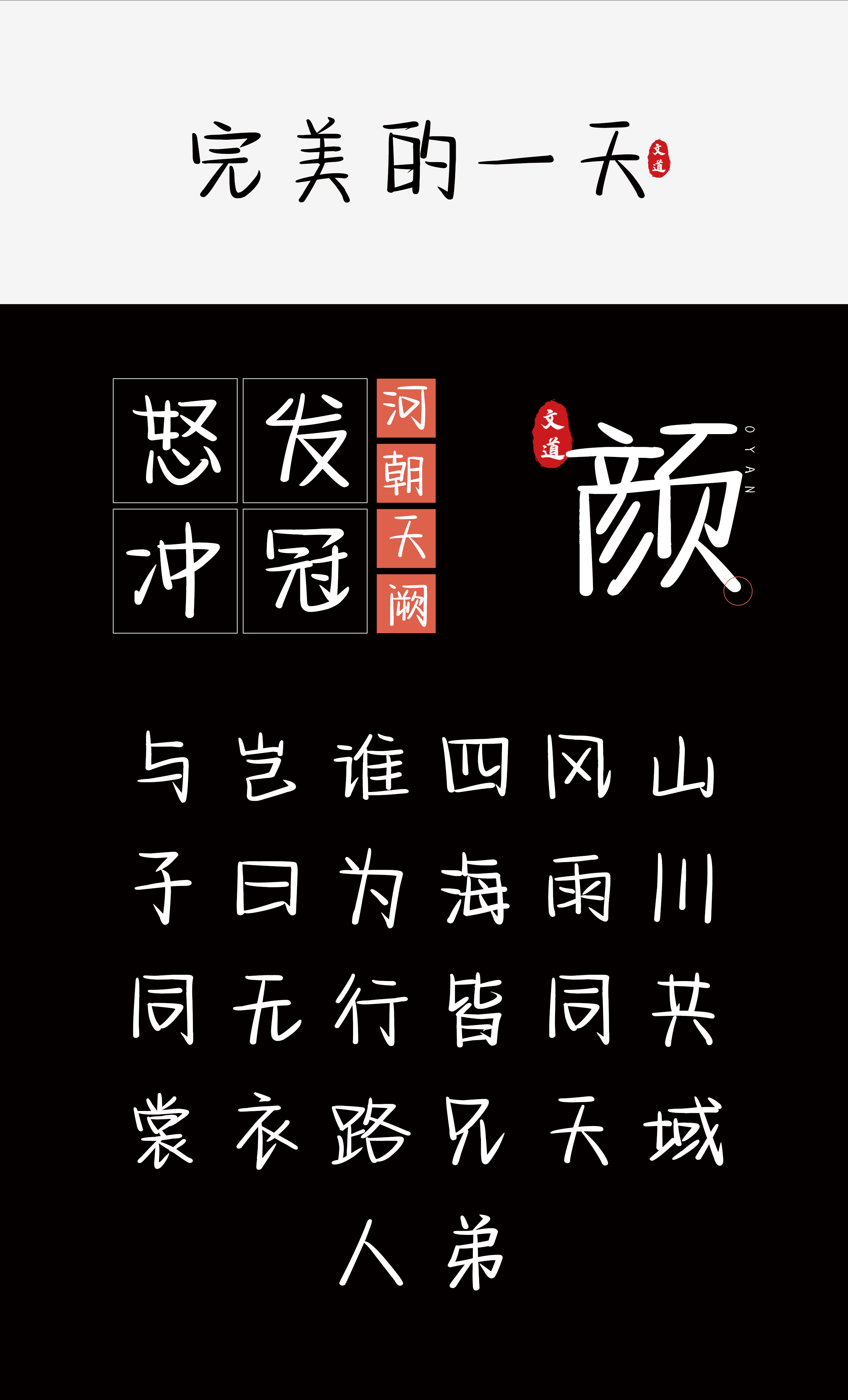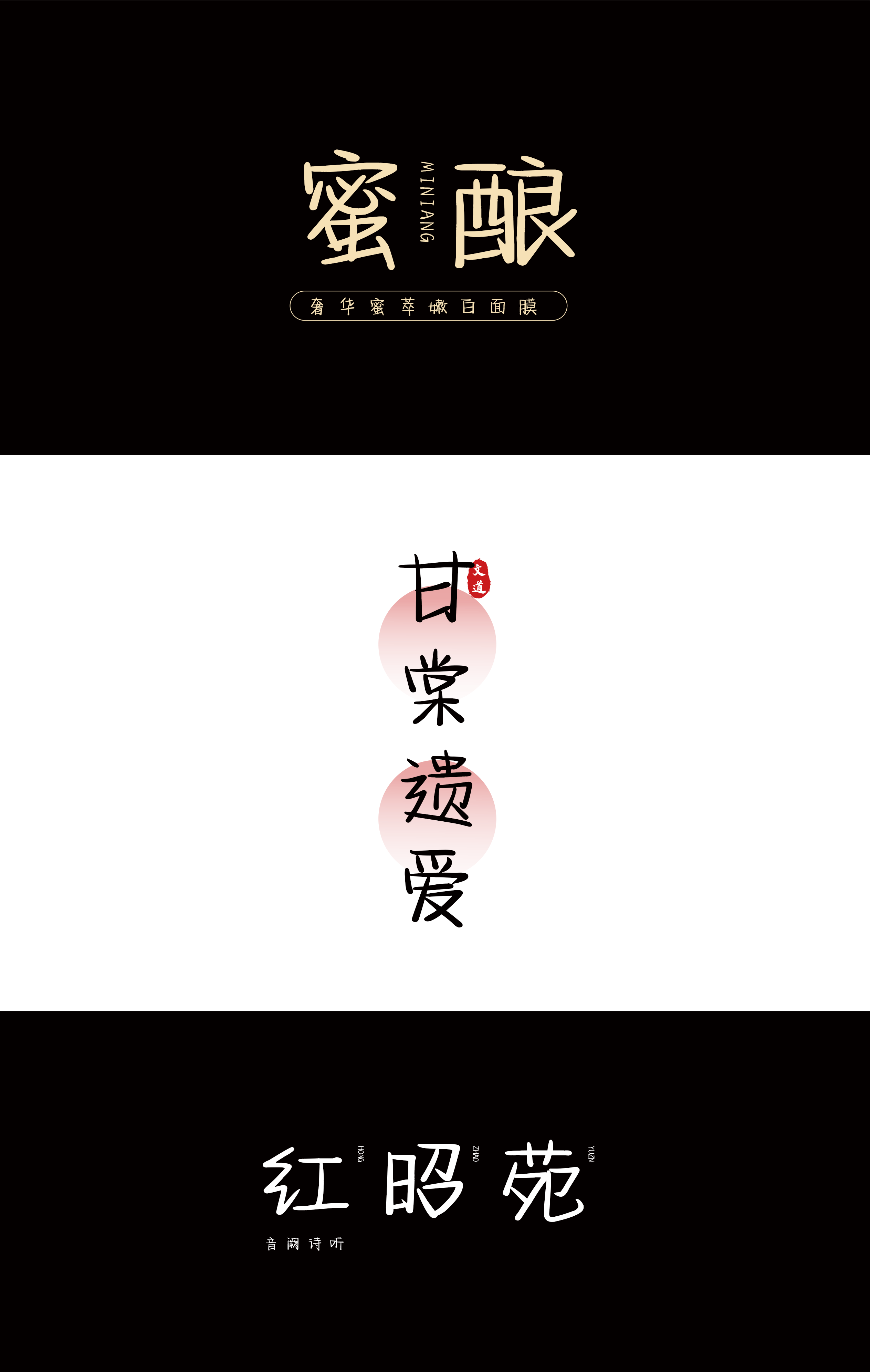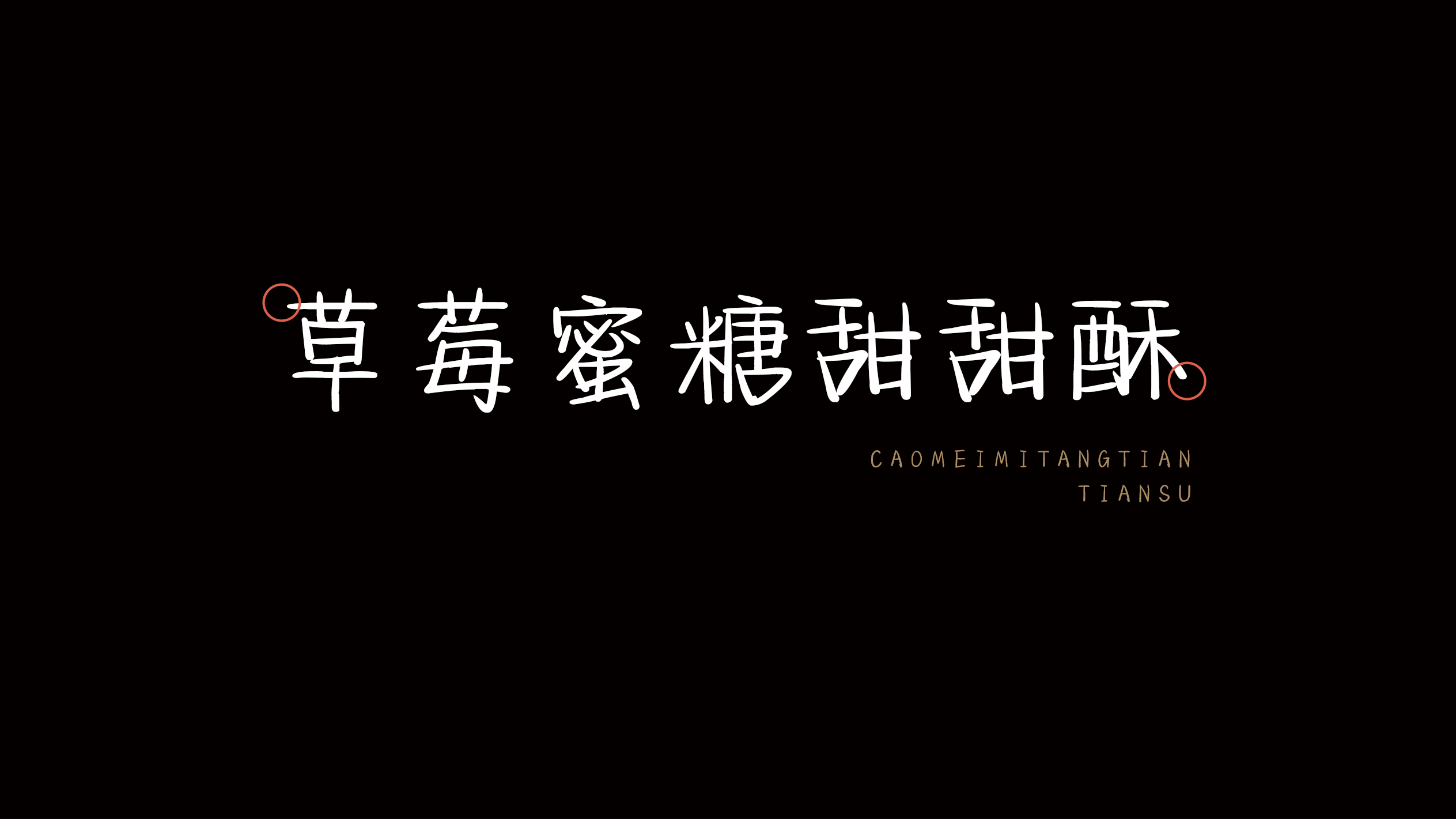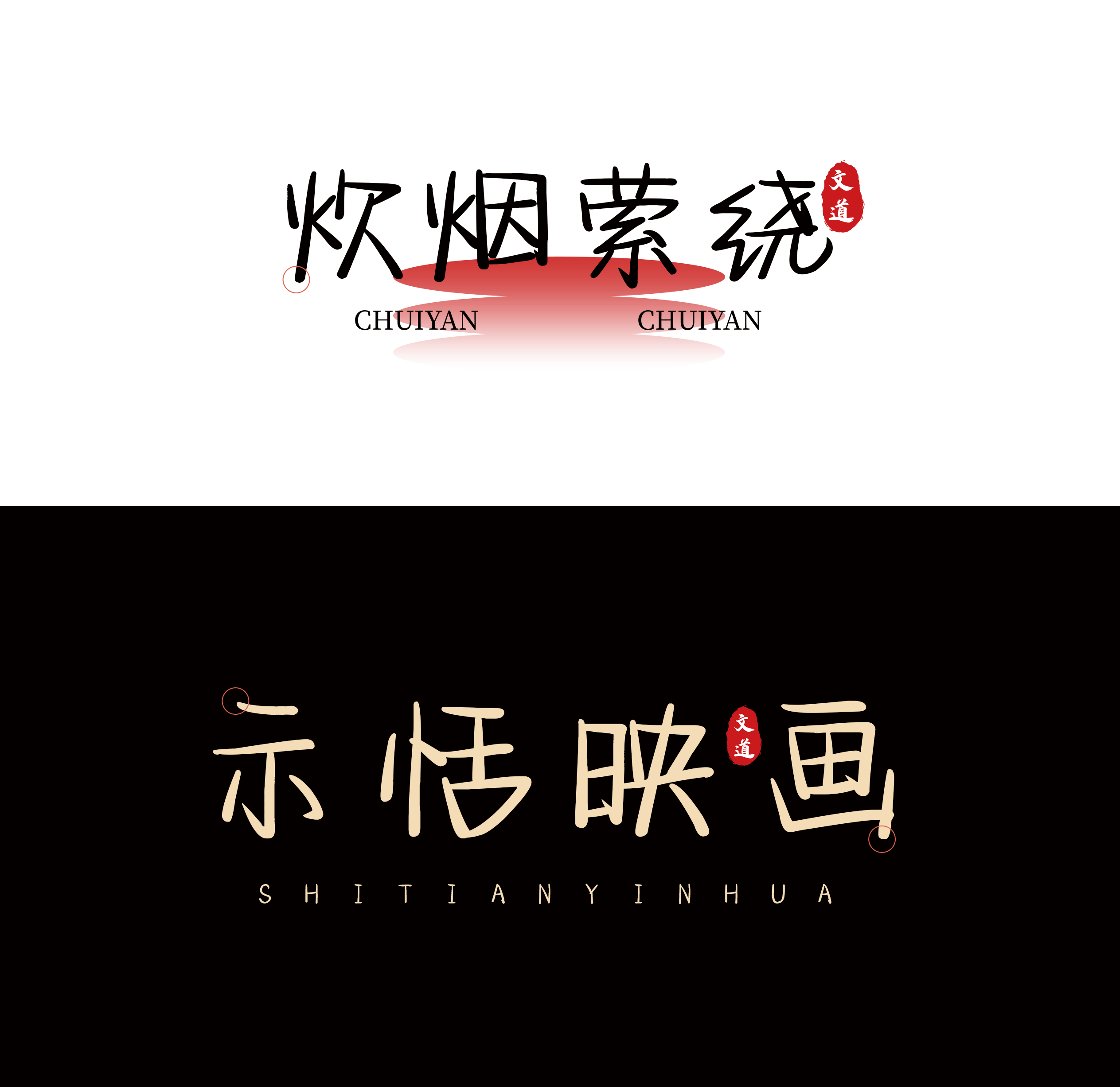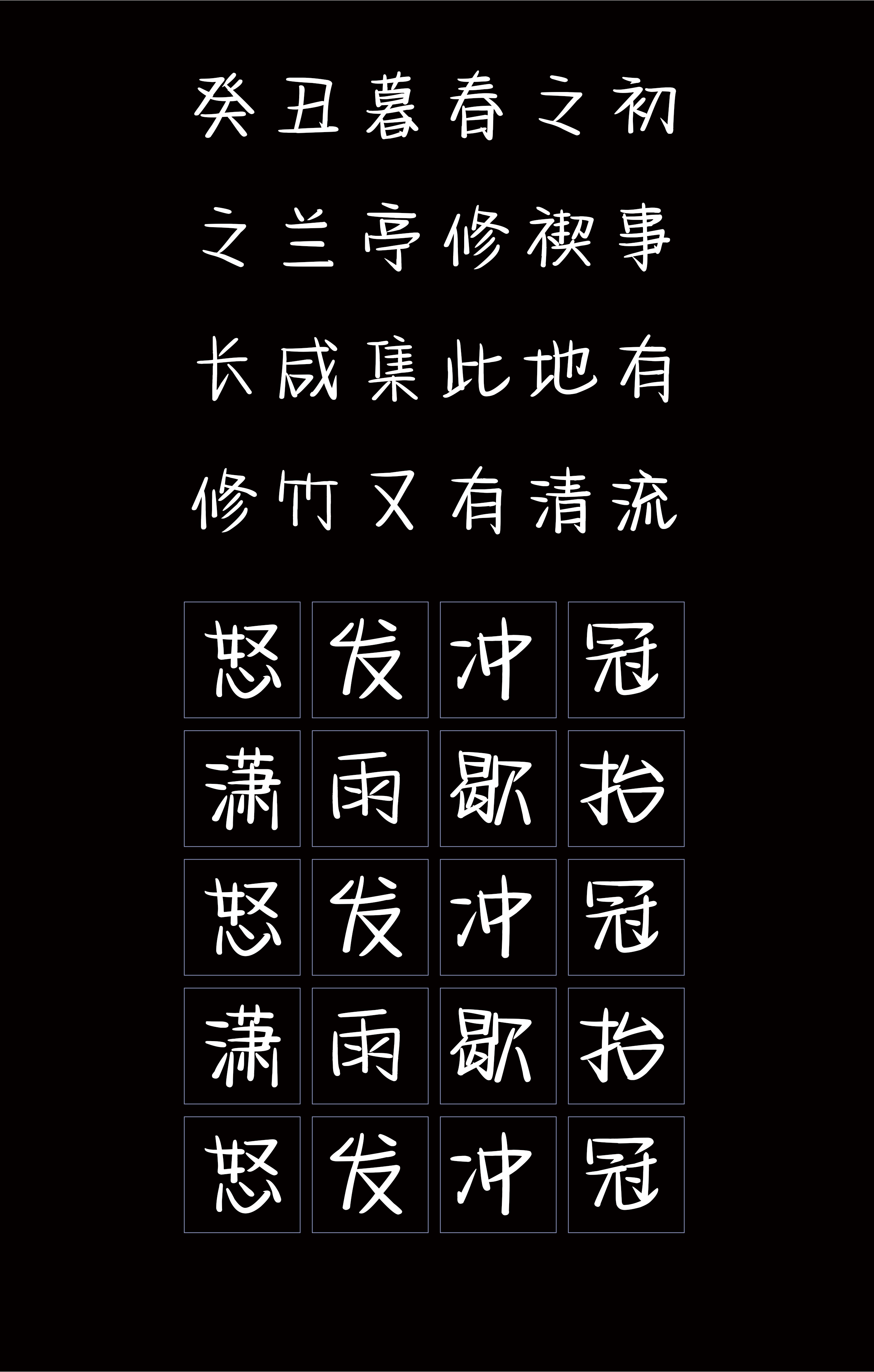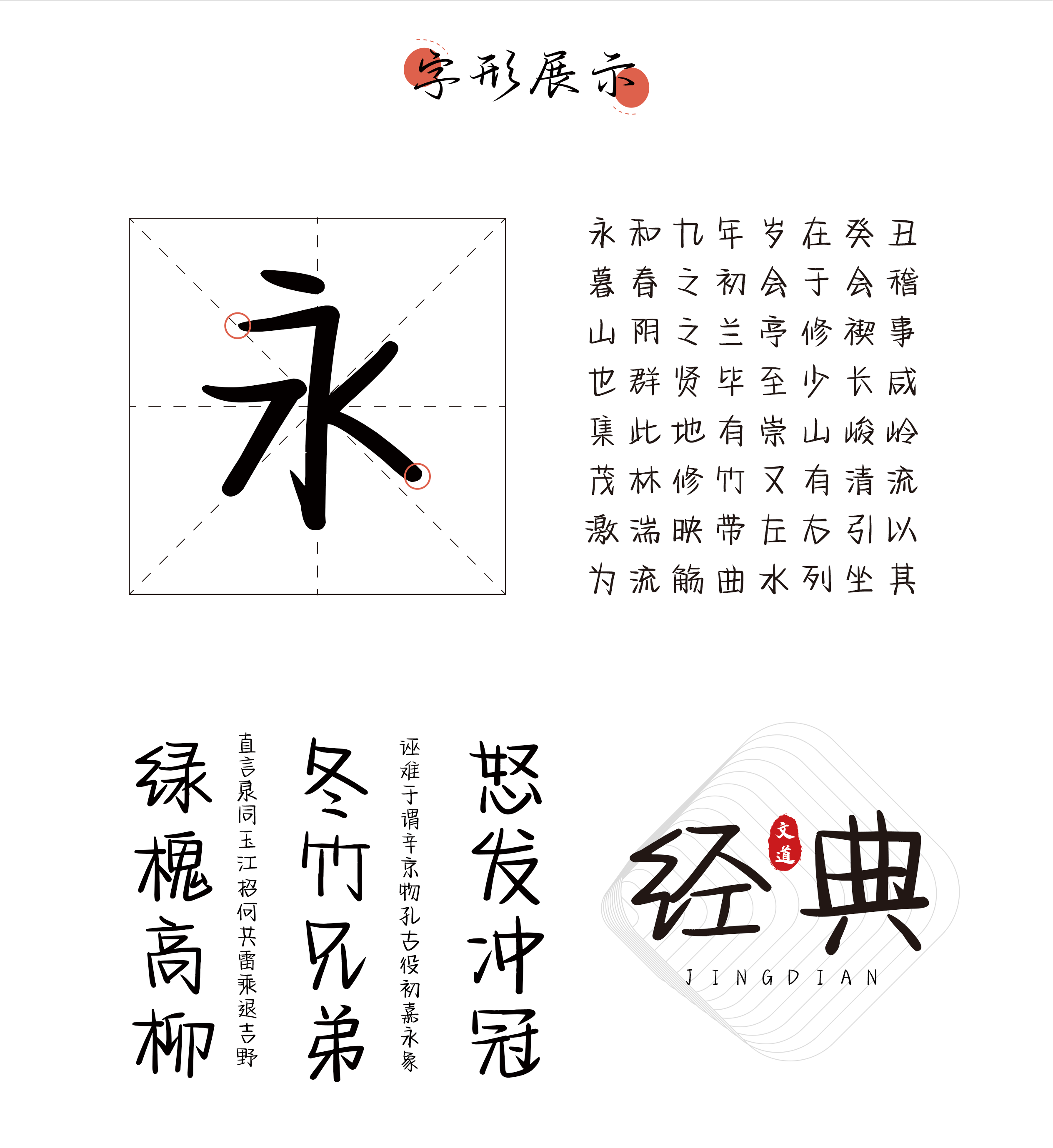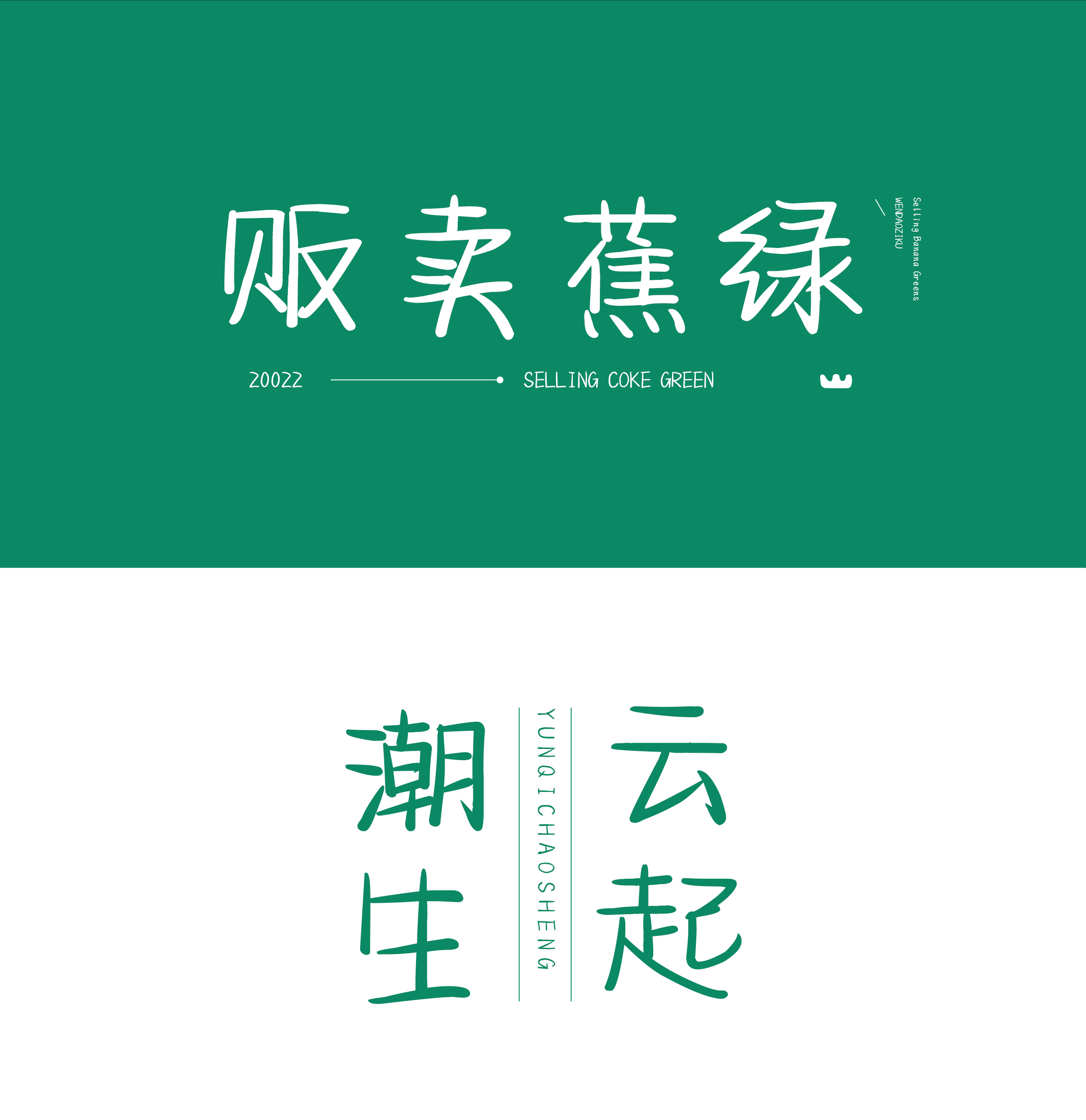
草莓舒芙蕾
字体名称: 草莓舒芙蕾
所属分类: 可爱 手写
字符集: 简体字符 字母 标点符号 数字
适用场景: 广告 电商 新媒 影视 海报 动漫
简介: 草莓舒芙蕾这款字是一款圆润可爱的手写体,字体笔画圆润可爱,整体字体活泼可爱,有一种天真无邪的感觉。适用于儿童类品牌广告和产品包装设计,也适用于创意海报设计。